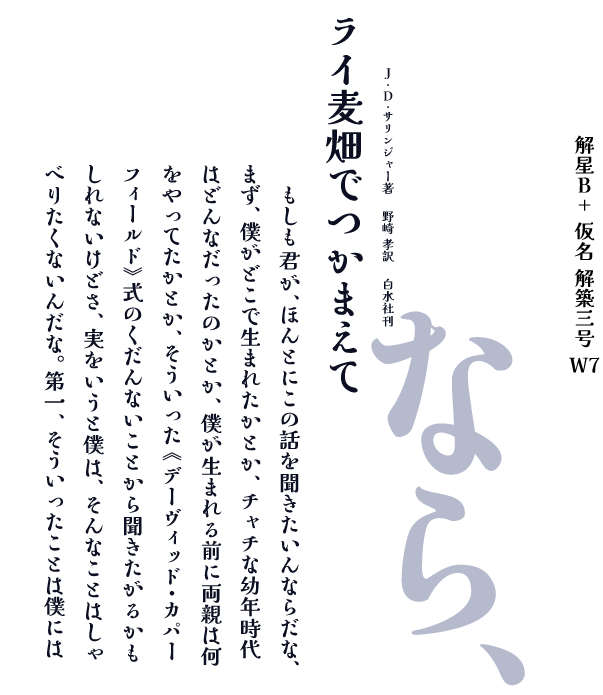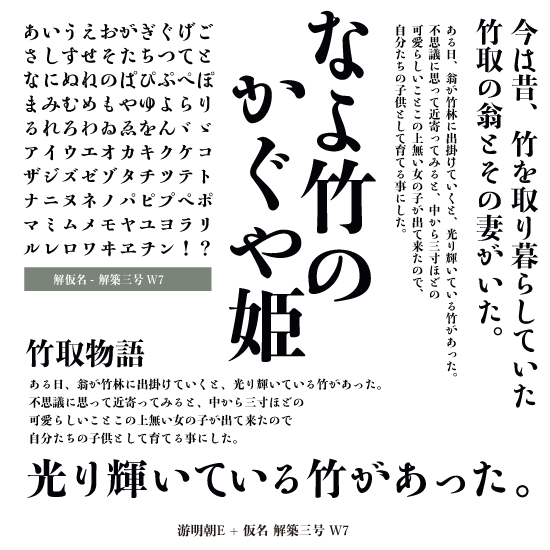
解仮名- 解築三号 W7
◉築地活版製造所のこの平安調書風をしのばせる細い三号仮名は、同様の一号とともに多く使われました。楷書などとも組まれています。書を日常とした先人たちは、連綿する書の息吹の中から一字一字を独立した正方形の金属字形として見事に誕生させました。「解築三号細かな」は、築地活版製造所の三号仮名を基に明朝体や楷書など現代の電子組版状況と違和感無くお使いいいただけるように仮名の比率や濃度バランスを調整しています。汎用性の高い身近な書体としてお使い頂けるよう翻刻しました。